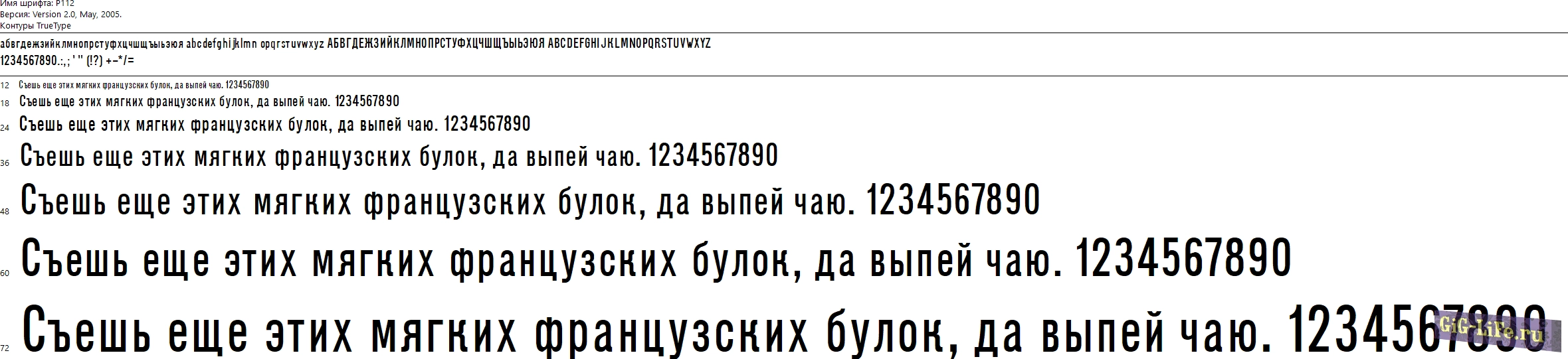
У нас есть коллекция основных шрифтов (TTF), которые используются для надписей на топографических планах и картах. Это очень полезный инструмент при создании топографических планов масштабов 1:500, 1:1000, 1:2000, 1:5000.
- A431.TTF - шрифт А-431 (Академический курсив),
- BM431.TTF - Бм-431 (БСАМ курсив малоконтрастный),
- BO2.TTF - Бо-2 (БСАМ курсив остовный),
- CH122.TTF - Ч-122 (Четкий суженый полужирный),
- CH131.TTF - Ч-131 (Четкий),
- CH132.TTF - Ч-132 (Четкий полужирный)
- D231.TTF - Д-231 (Древний курсив прямой),
- D431.TTF - Д-431 (Древний курсив),
- D432.TTF - Д-432 (Древний курсив полужирный),
- DO431.TTF - До-431 (Древний остовный курсив),
- P112.TTF - Р-122 (Рубленый узкий полужирный),
- P131.TTF - Р-131 (Рубленый),
- P151.TTF - Р-151 (Рубленый широкий),
- P152.TTF - Р-152 (Рубленый широкий полужирный),
- T1_131.TTF - Т1-131 (Топографический 1 (цифры),
- T2_131.TTF - Т2-131 (Топографический 2 (цифры),
- T132.TTF - Т-132 (Топографический полужирный).